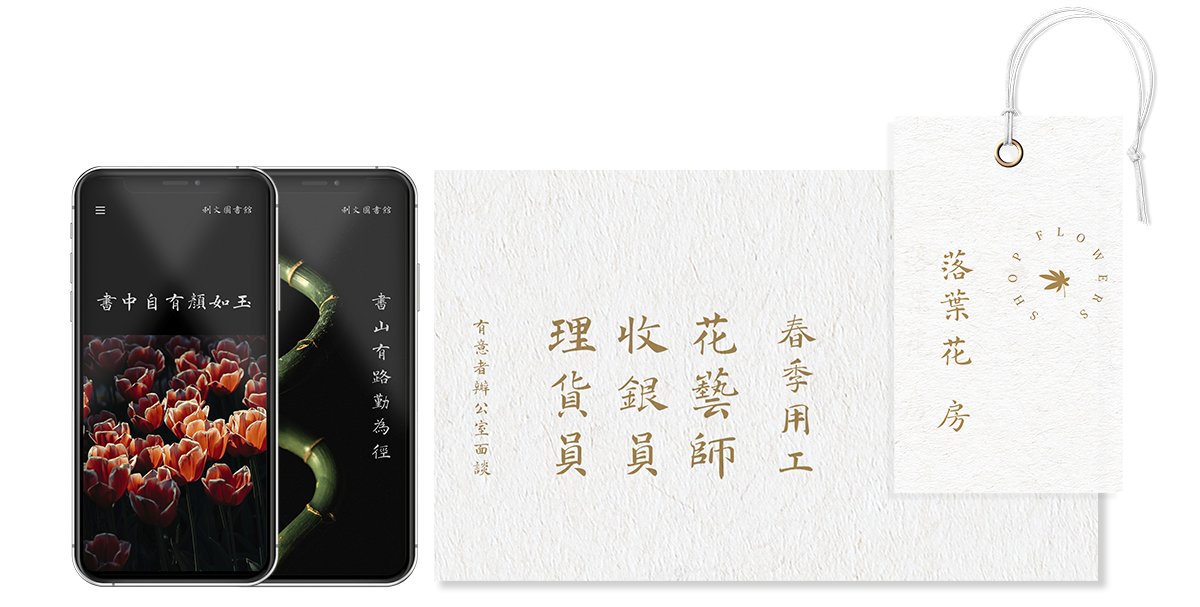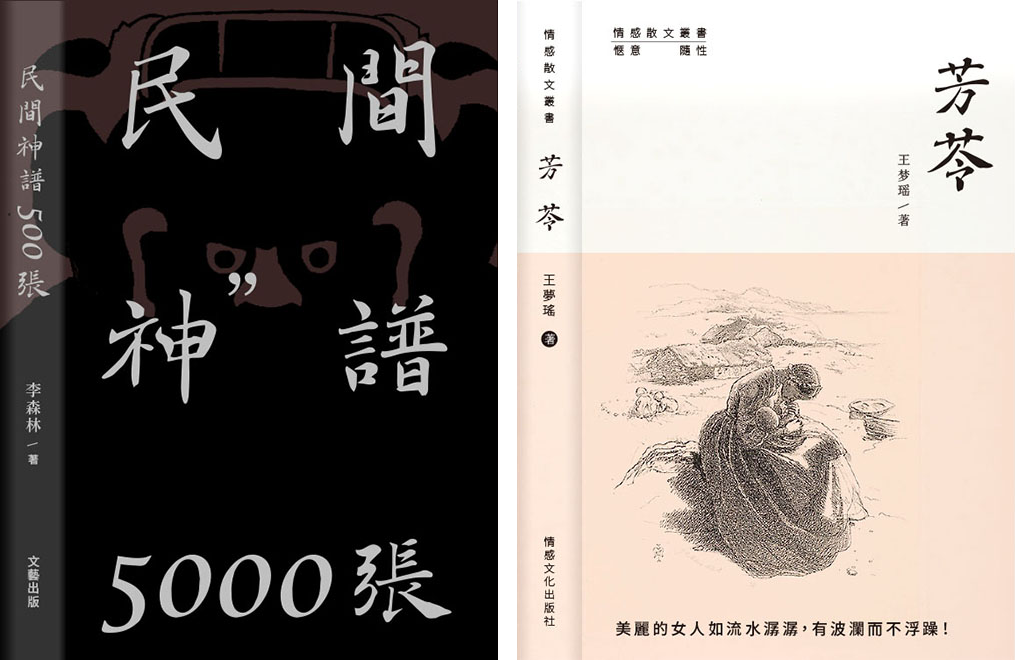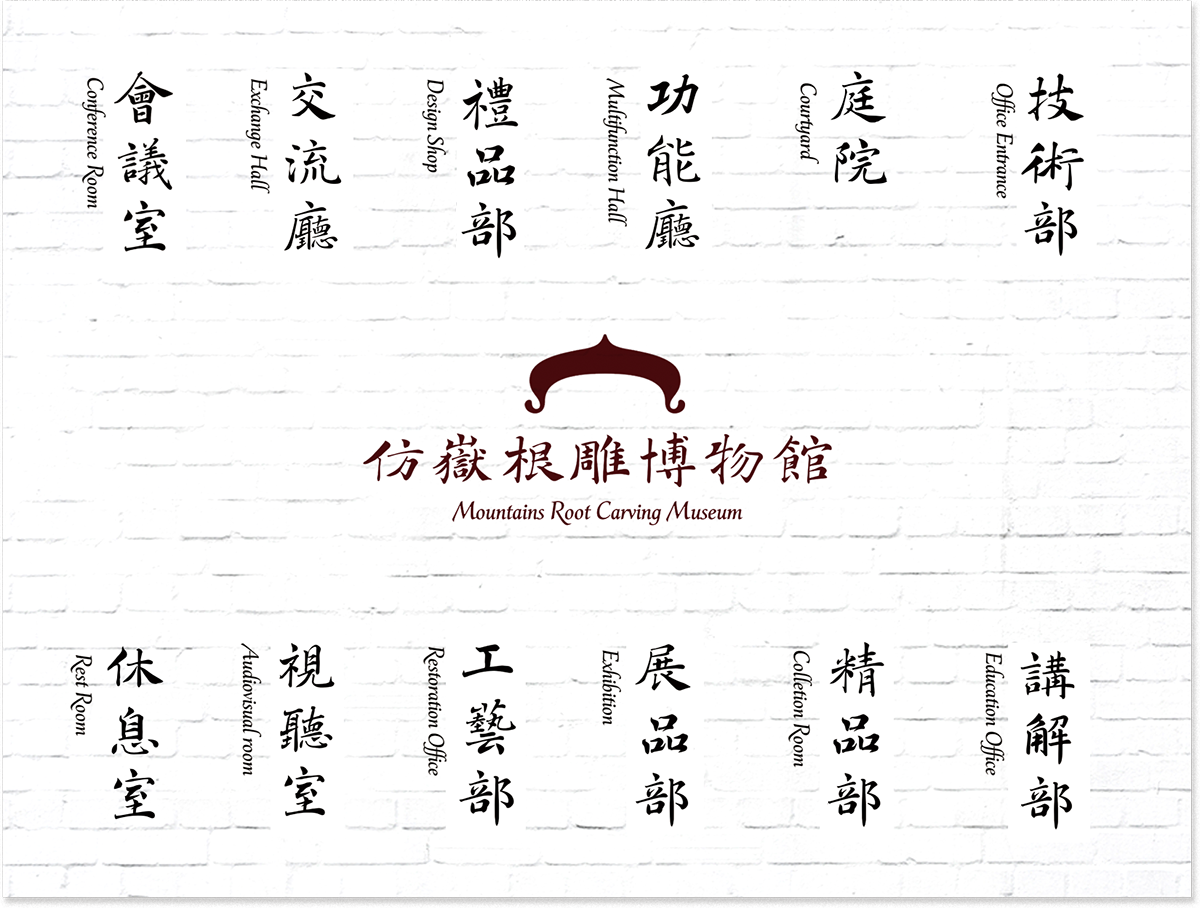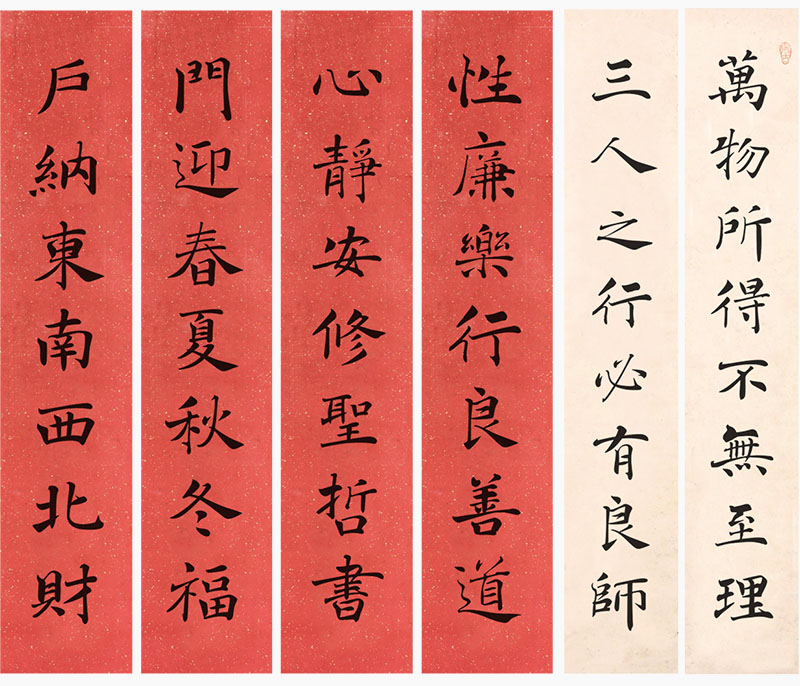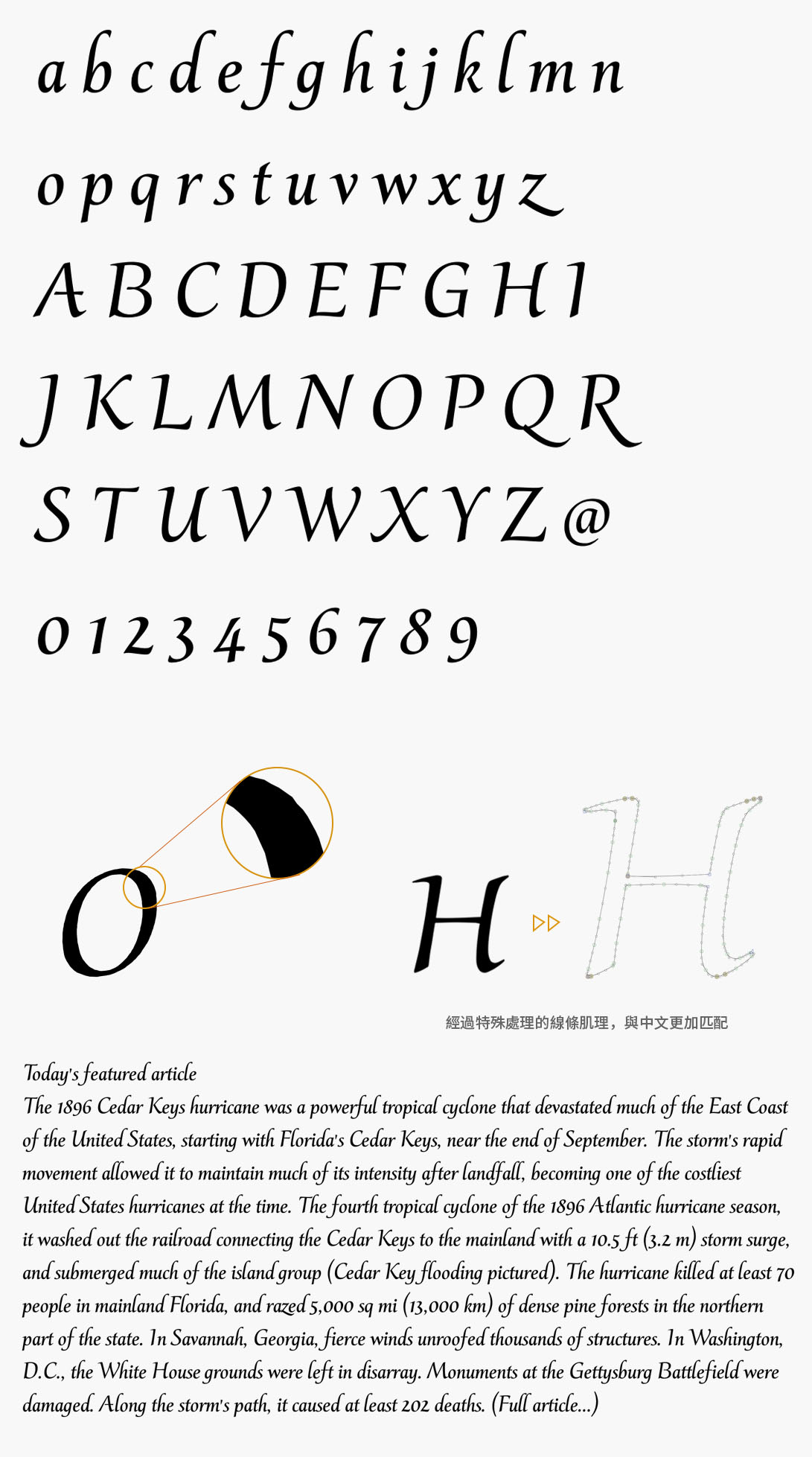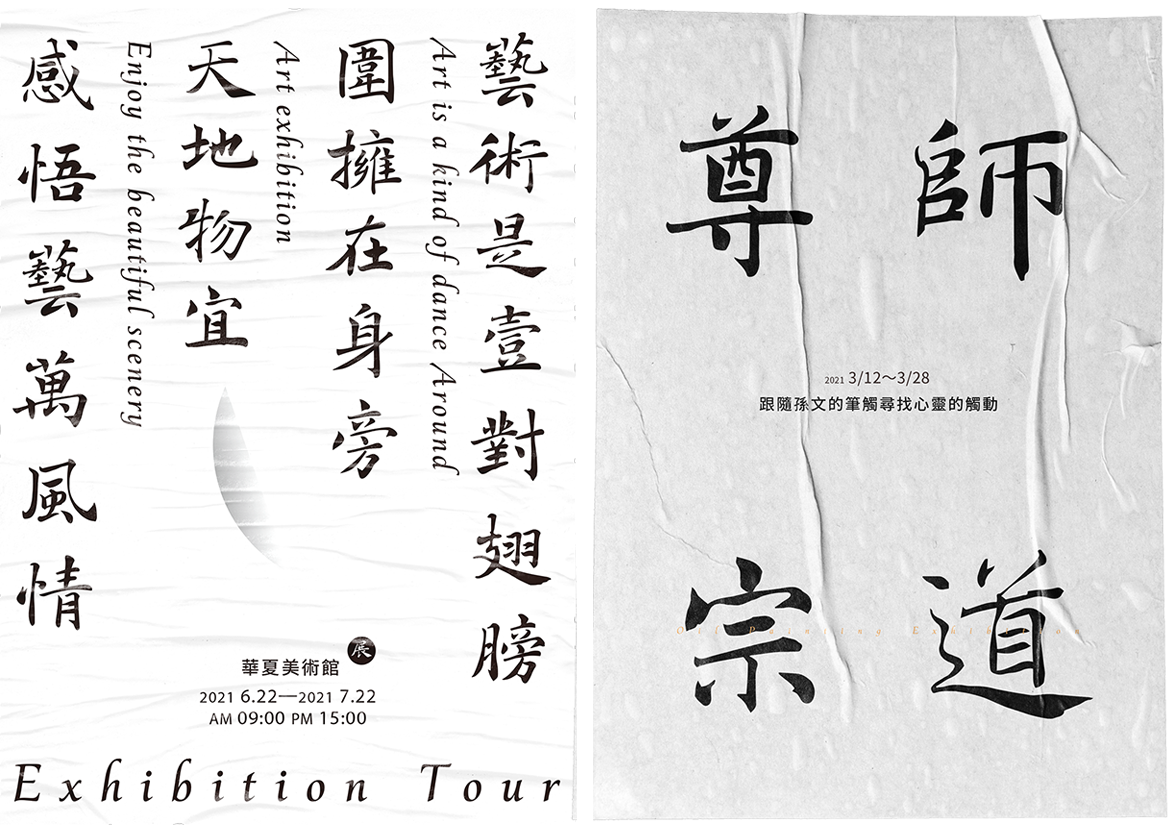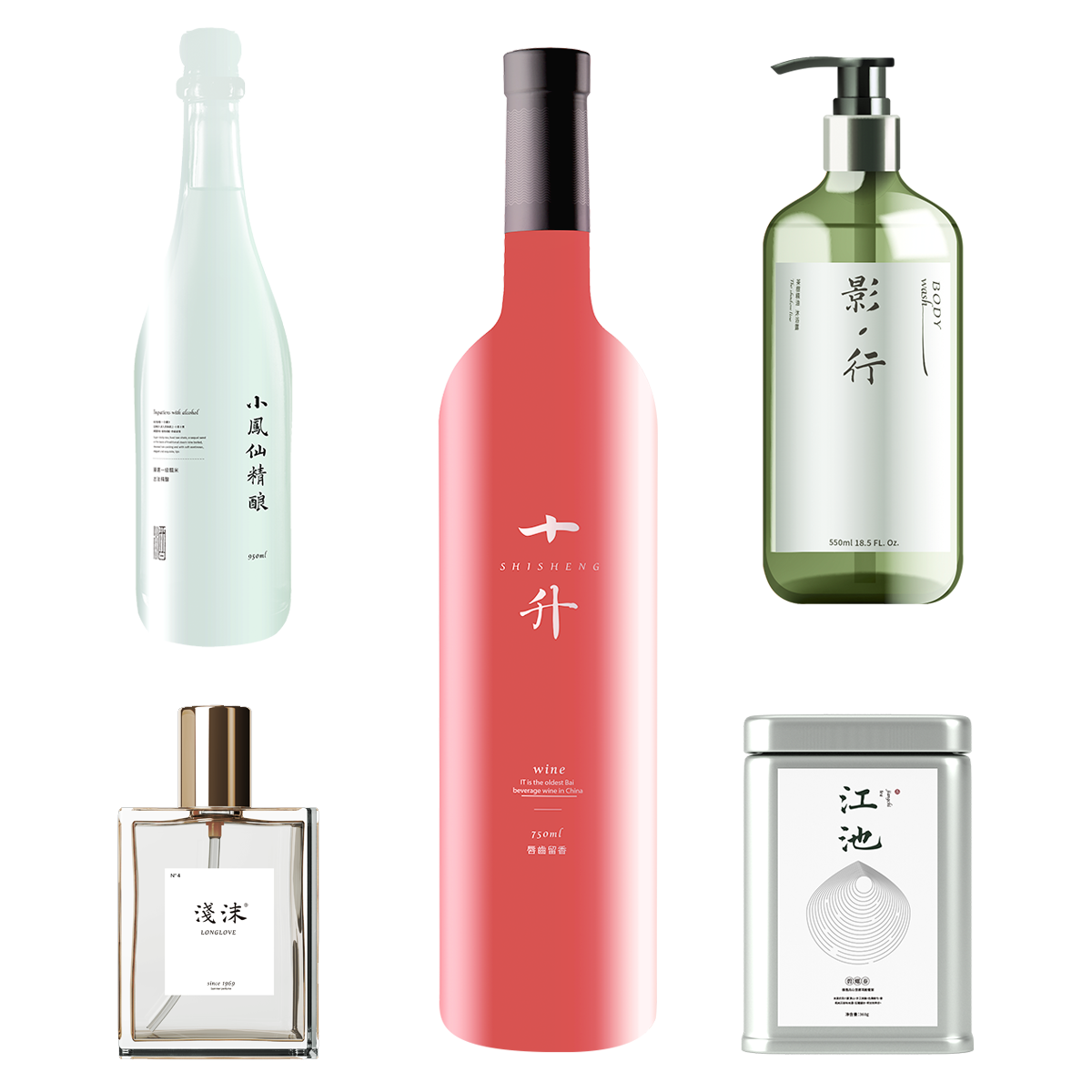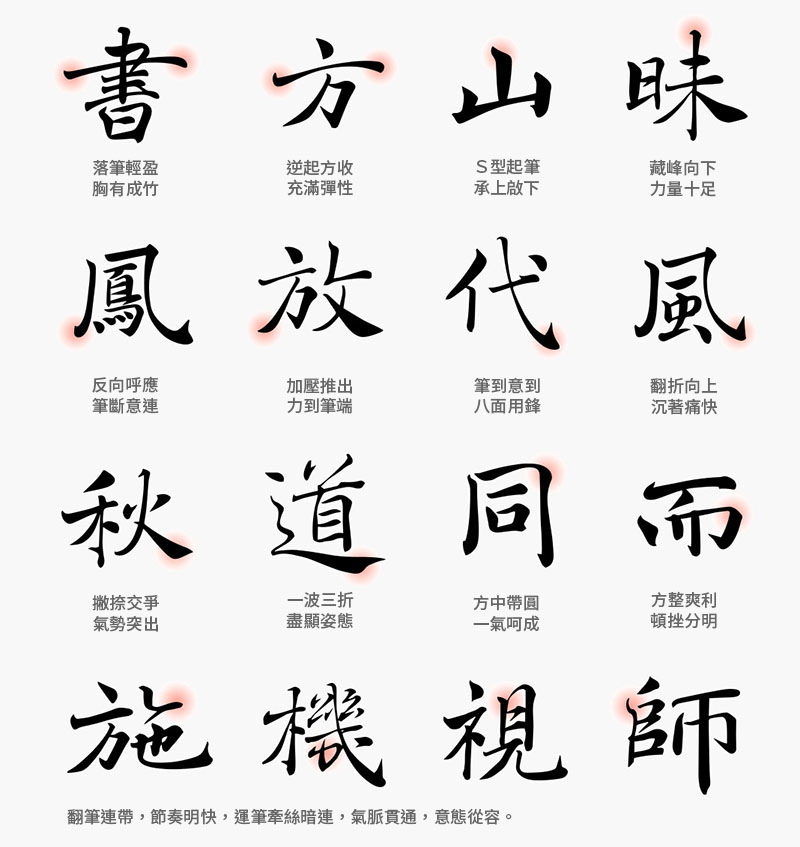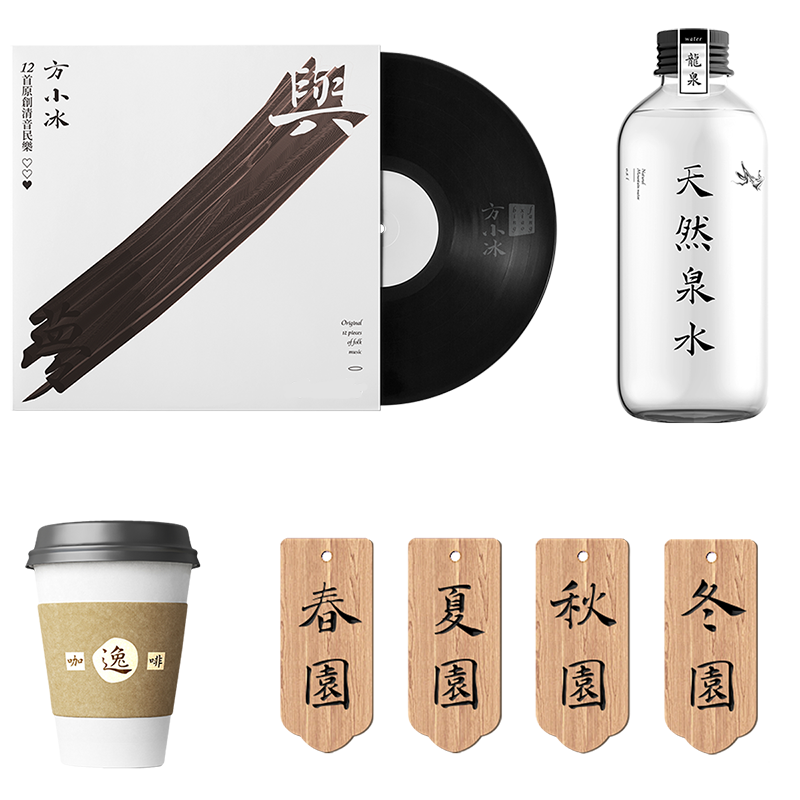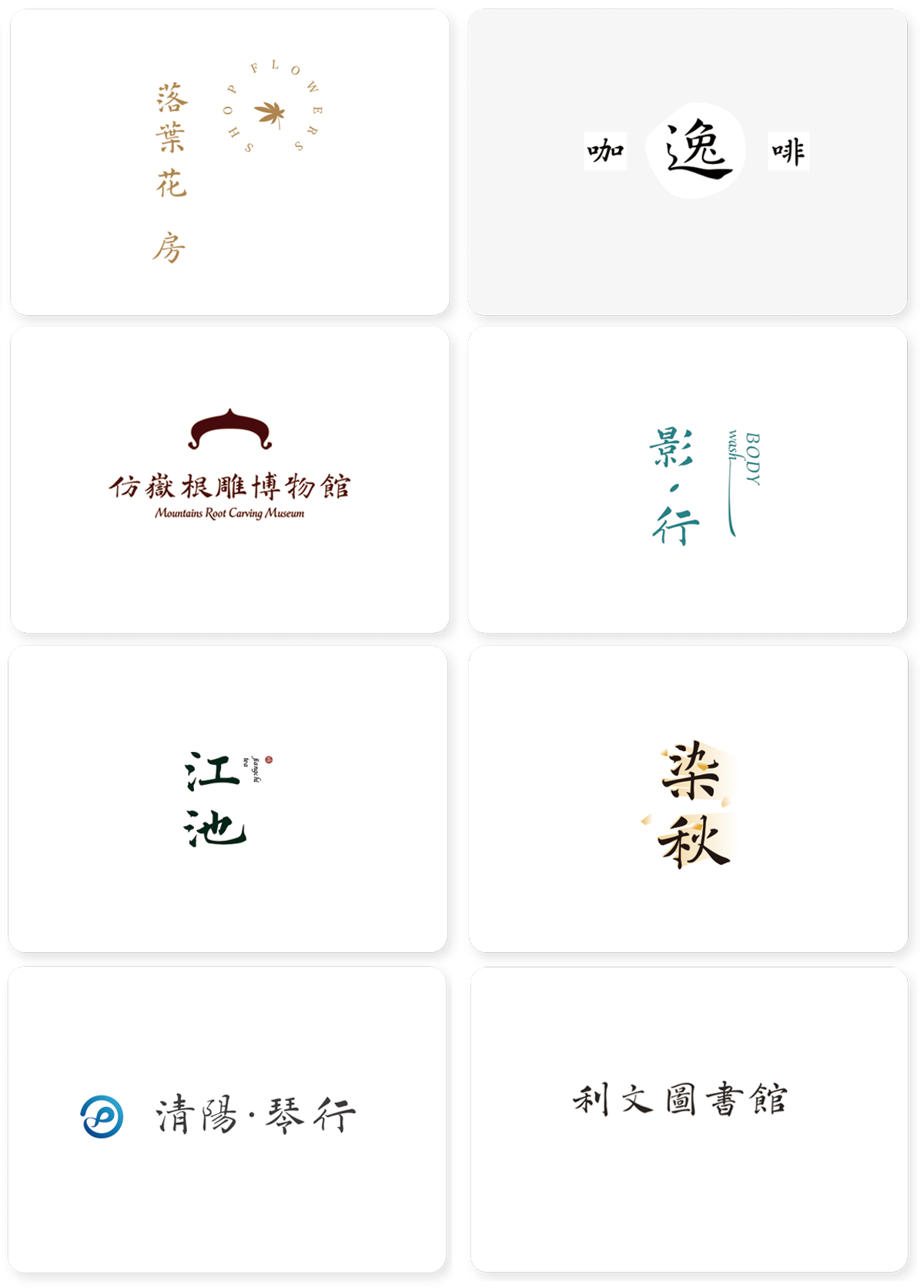
楷中蘭亭現在大約有8500個字。
楷中蘭亭 兼具法度與靈動的藝術楷體
外在自由輕鬆,空靈瀟灑;內在胸有成竹,千錘百煉的通用高品質楷書字型。
我們從小接受的美育和各種潛移默化的文字審美,特別是電腦字型的應用和推廣,導致我們對楷書的印象大多停留在形體方正、筆劃平直的美感範疇。
古人云:“取法乎上,而得乎中;取法乎中,而得乎下。” 作者從事設計並熱衷字體多年,在與古人對話的過程中經常會思考楷體的多面性:能不能創造出既有楷書的法度而又不會過於嚴肅,既有行書的靈動而又不會媚俗的高品質字體。它必須具備電腦字型的基本屬性,同時又符合現代的應用審美,尤其是用戶感觀上的自由、輕鬆和無拘無束的狀態。
現在學書,寫字,做字,從深入瞭解傳統文化到創造出符合時代特點的字型產品,越來越覺得有義務也有必要去做經得住時間考驗的上乘產品。這正是我們創作《楷中蘭亭》的初衷和願景。
《陰符經》
楷中蘭亭的特點介紹
No.1 楷行結合,空靈瀟灑
《楷中蘭亭》取法陰符經和雁塔聖教序,行化比例恰到好處。既有靈動瀟灑的一面又具備正統法書的嚴謹楷模。既有完備的楷書範則又有變化多姿的細節表現。總體結構方中見扁,多為橫勢。運筆牽絲暗連,節奏明快,線條對比強烈,恰當參入隸書筆意以現高雅古樸。
No.2 用筆靈活,跌宕多姿
《楷中蘭亭》在設計師的眼中它是圖形、是符號、是跳動的音律。在書法家的手中是書寫、線條、情性的表達。在應用者的手中它本身就是一件藝術品,能夠快速抓住用戶的共鳴。然而想開發成電腦字型要做的更多是在“活字”內容的枷瑣下,把它們巧妙的融合貫通直到全套標準。
No.3 對比強烈,節奏鮮明
《楷中蘭亭》十分注重文字的書寫性,把筆的內容發揮到極致,粗細、曲直、開合、長短、連斷等等辯證關係表達得混然一體,從而形成獨特的文字視覺美感。對於想表現文化、生活、教育、藝術等方面的品牌和產品有著與生俱來的優勢和魅力!
No.4 變化多端,和而不同
《楷中蘭亭》嘗試在電腦字型和書法的雙重內容中找到一個臨界點,比如用筆的多樣性,字法的看似相似,實則不同。相比傳統書法字體放大使用時的雜質和粗糙感,以及電腦字形過於光滑而達不到的自然肌理,楷中蘭亭從應用角度出發,保留部分書法線條的肌理,並適當新增線條的光滑度,放大使用細節豐富,耐人尋味,縮小使用肌理適中,節奏明快。
各種應用均有良好的表現
《楷中蘭亭》獨具美感,只需簡單安排。各種應用場景均能輕鬆應對。如:招牌、選單、名片、海報、書籍、飲品、食品包裝、字幕等楷中蘭亭都能靈活應用。
《楷中蘭亭》是設計師聯合書法家共同創作設計的,目的是找到電腦字型和書法的完美結合,在取到書寫方案後會挑出部份文字多次重寫。然後進入漫長的字形檔內容的反復修改與調整,並最終接近理想中的樣子。
楷中蘭亭的專屬歐文字母
歐文單獨放置也有舒適的閱讀流暢度和版面肌理,與中文相得益彰。
楷中蘭亭是字型設計作品,也是一件值得收藏的書法作品和臨摹字帖
字庫版《千字文》